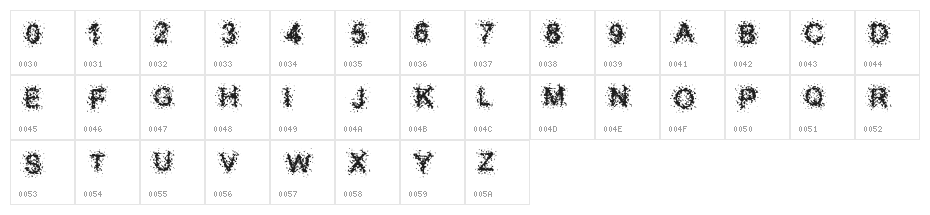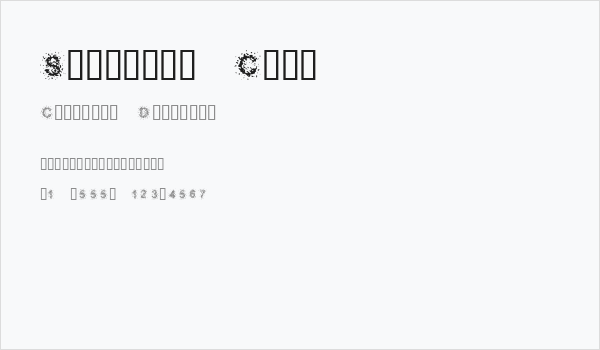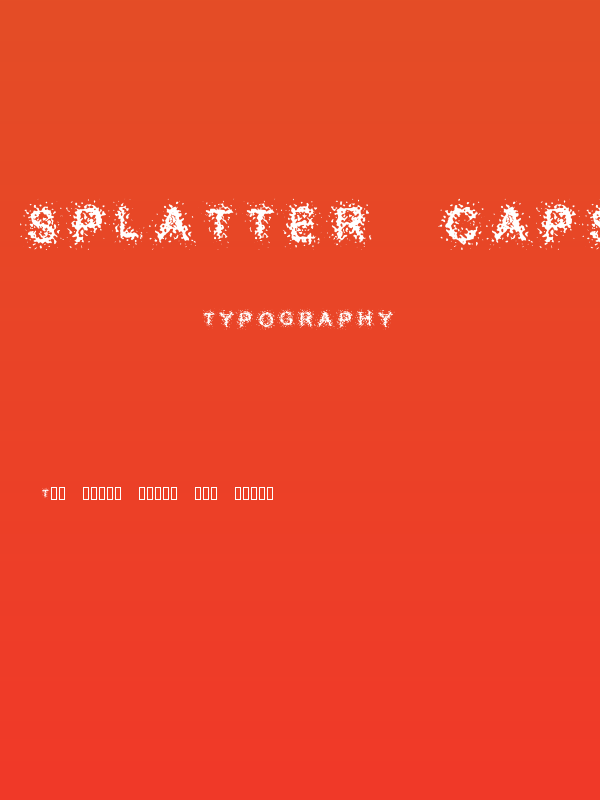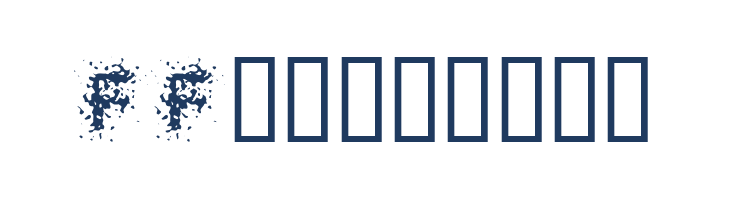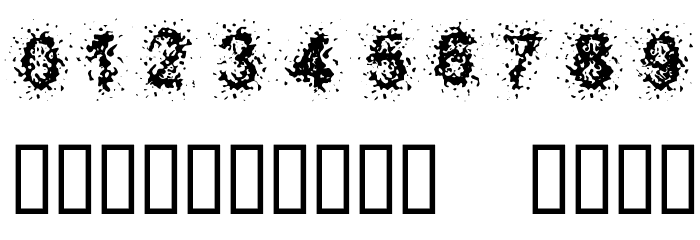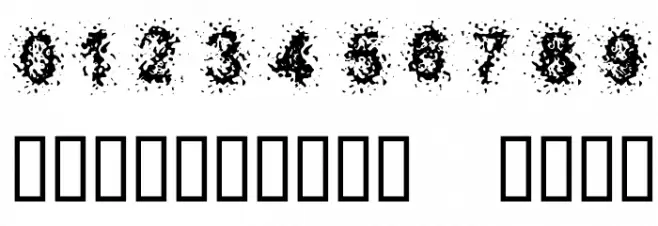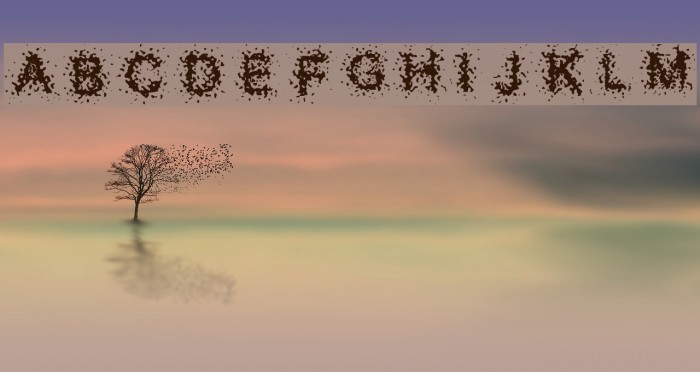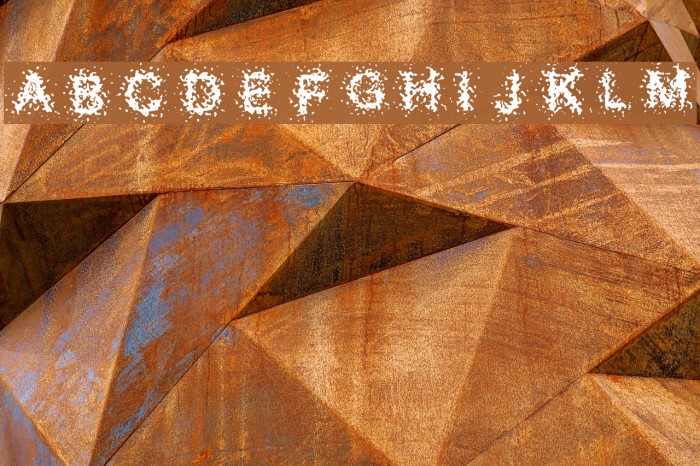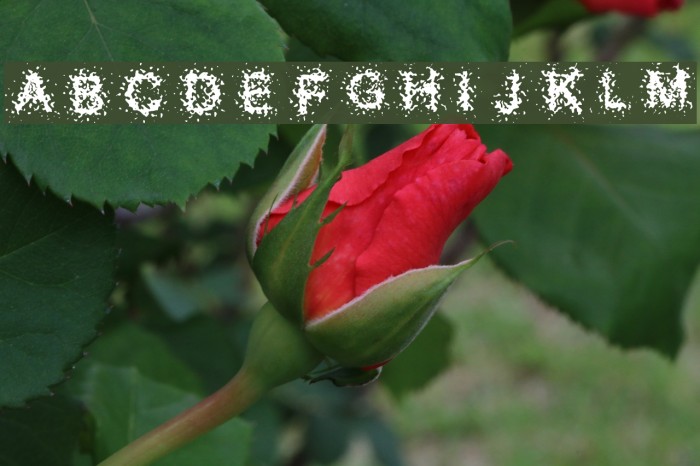
Splatter Caps Font
| حالة الاستخدام | Headlines, Posters, Artistic Designs |
| مشاريع مقترحة | This font is perfect for album covers, event posters, street art designs, and any project that requires a bold and artistic statement. |